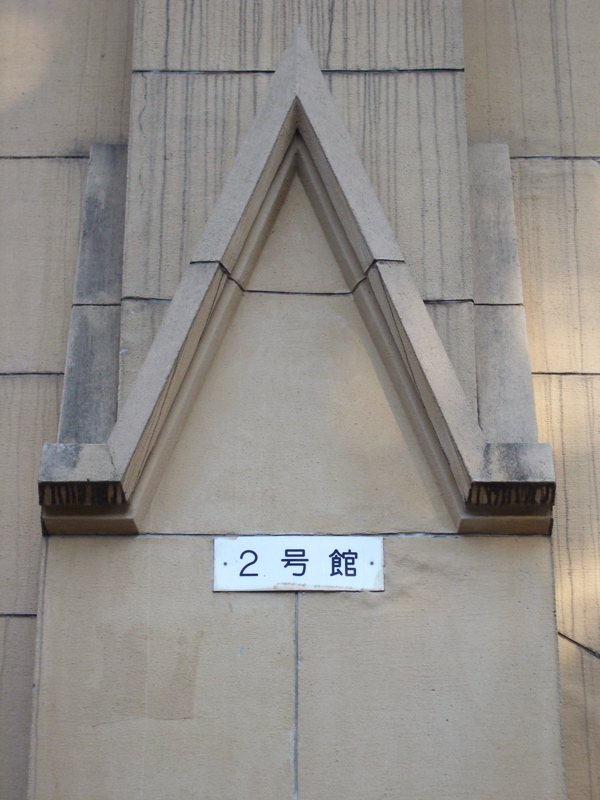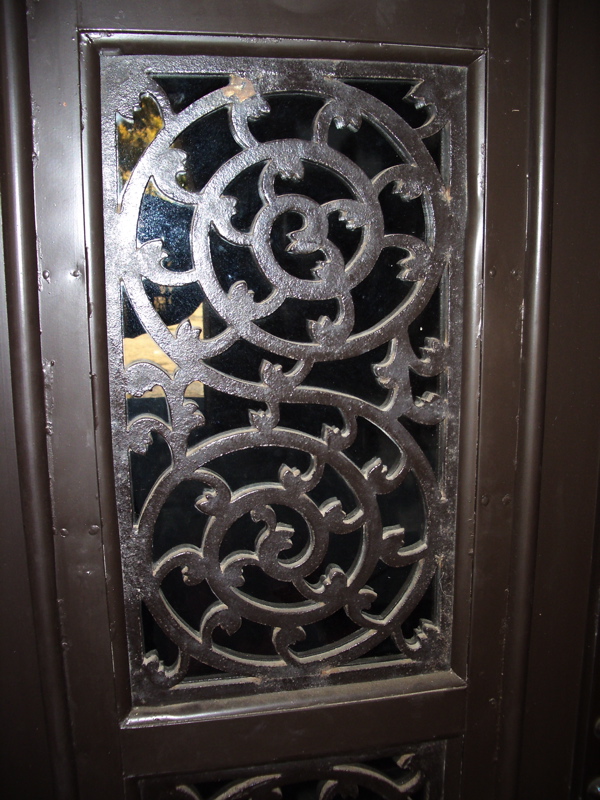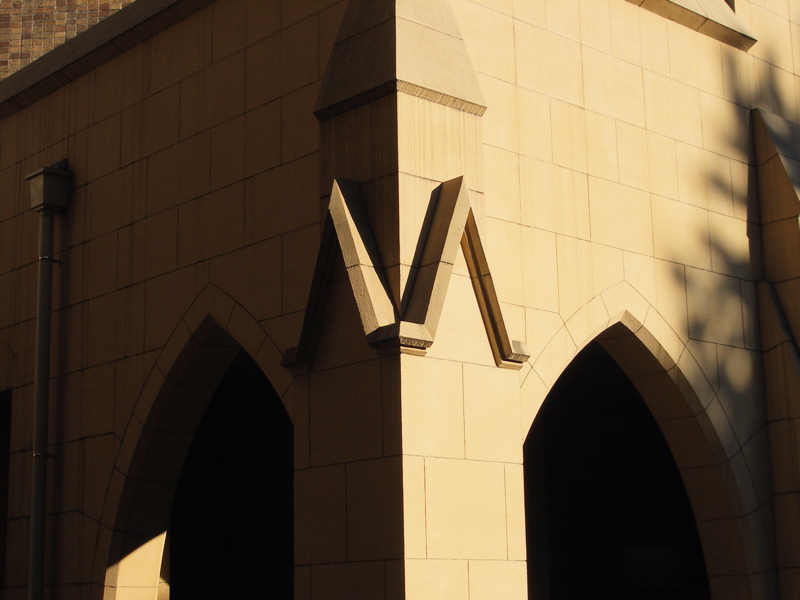
東大の中のアルファベット
休日の犬の散歩コースである東大構内は、今イチョウがまっ黄色に燃えています。
年が明けるとすぐにセンター試験があるので、そろそろ下見に来る学生さんもいますよね。(受験生諸君!頑張れ〜)
東大構内の建物は新しいものもありますが、ほとんどはレンガ作りで歴史の古そうな物ばかり。
ジャジャ〜ン、その中でアルファベット発見! 農学部の2号館にはAとMが!
クロスバーがチト細いAですが文字のプロポーションは絶妙。MはAがふたつで 出来ています。普通、A二つを隣りに並べたのでは美しいMにはなりませんが、校舎の角に付けられたため、見る位置によって見事にMになっています。
おっと〜!入り口のドアにS発見!重々しいドアに美しい装飾のSがいくつも施されていました。 写本のイニシャル装飾にもありそうなデザインですね。